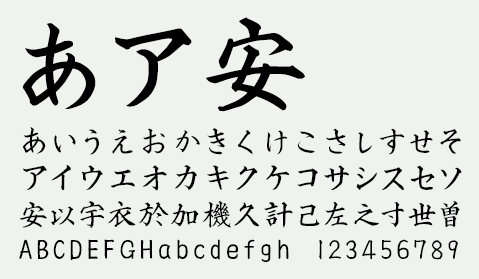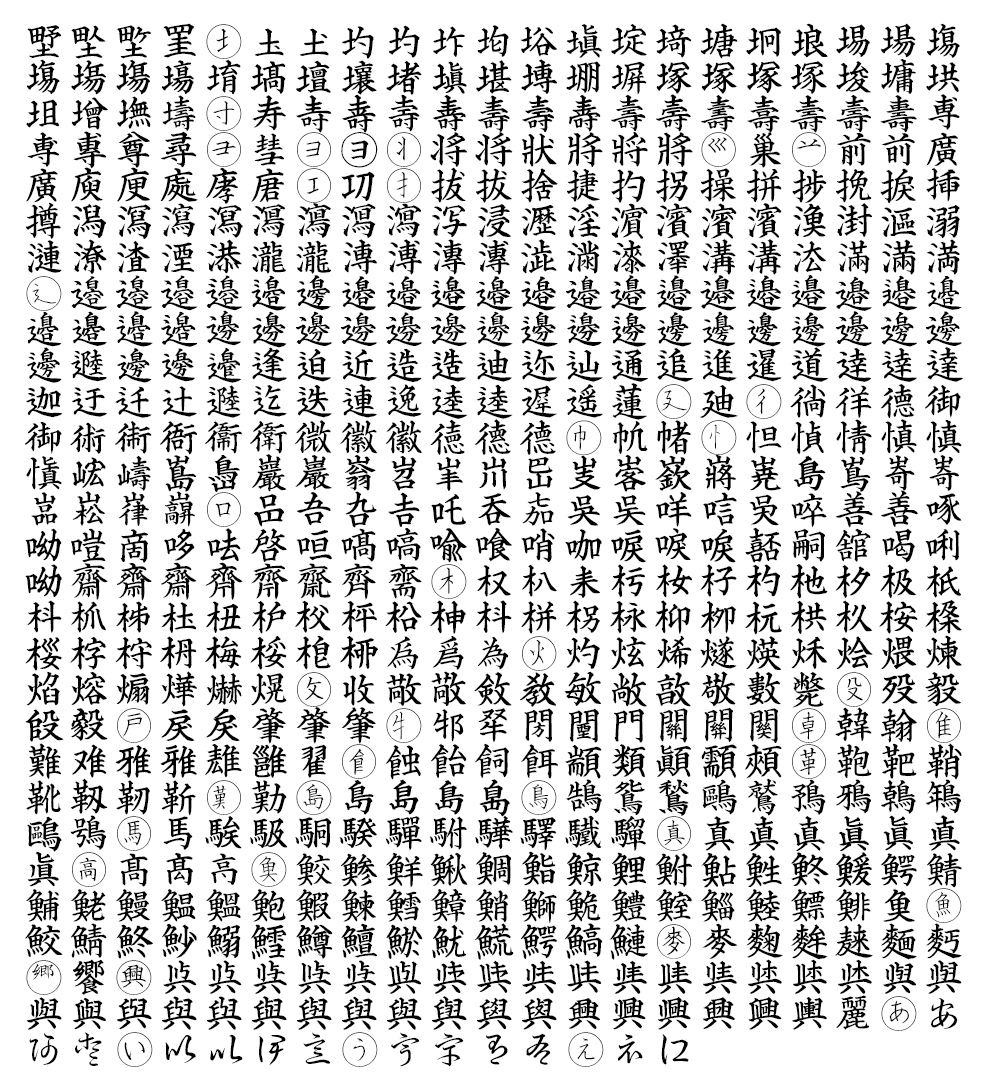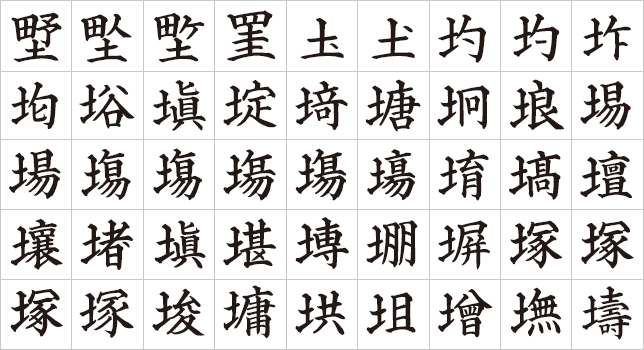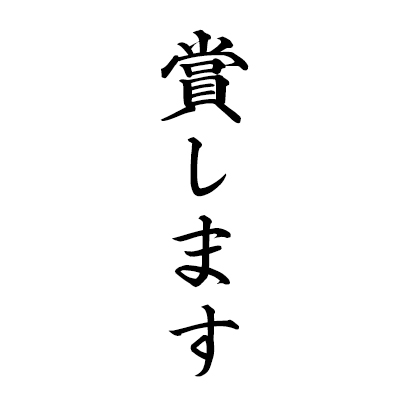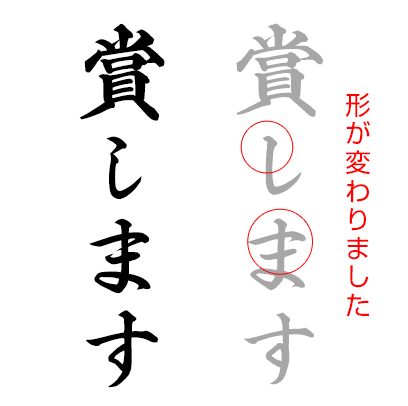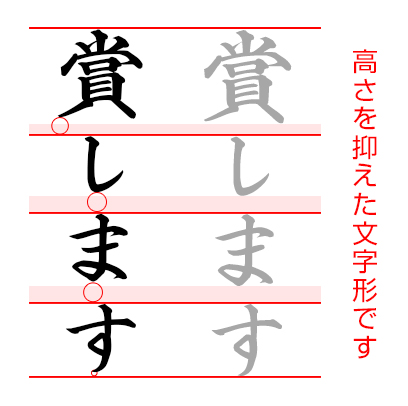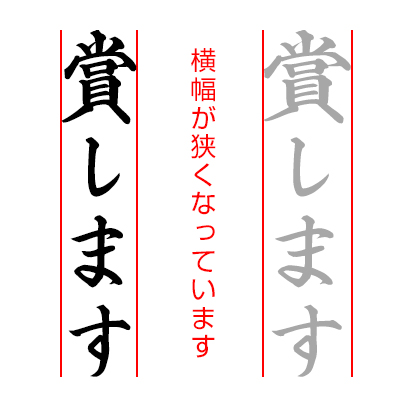
とめ・はねなど細部まで調整を重ねて開発された賞状専用書体
手書きのように高い品質の仕上がりをお約束します
NSK白洲賞状フォント
NSK白洲賞状フォント Cフルセット
フォント別特徴
ひらがな・カタカナ・漢字を使い分けることで、より美しい文字バランスを実現できます
NSK⽩洲賞状フォント (標準形) |
NSK⽩洲賞状表題フォント | NSK⽩洲賞状フォント 縦縮小 |
NSK⽩洲賞状フォント 横縮小 |
※上記はすべて同一ウェイトにて表示